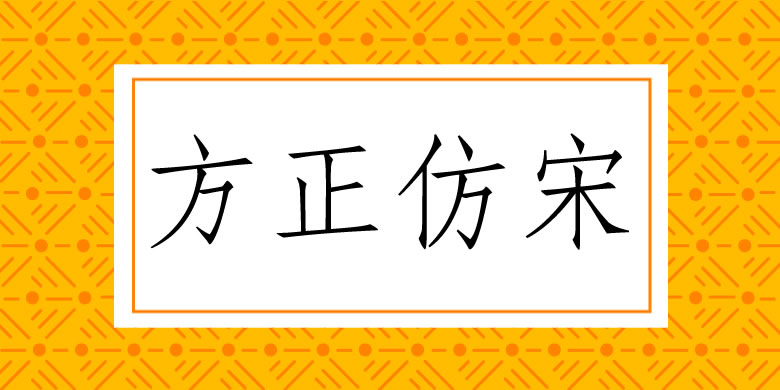
字体介绍 品牌:方正字库设计师:方正字模部发行时间:1996字库编码:大陆简体(GB2312-80)、大陆繁体(GB12345-90)、简繁扩展(GBK)、港台地区(BIG-5)分类:仿宋 英文名称:FZFSJW.TTF “仿宋体”产生于20世纪初,由当时的铅字制作者仿宋版书中的瘦细字体而制成。方正仿宋源于铅字时代的字稿,其字身略窄,笔画瘦硬,横竖笔画等粗,起笔处有斜势棱角,折笔处棱角分明,整体字形挺拔俊秀,给人以悦目之感。因清晰美观,容易辨认,长期被用于工程图纸文字和书刊中的引文。 字体下载 官方下载